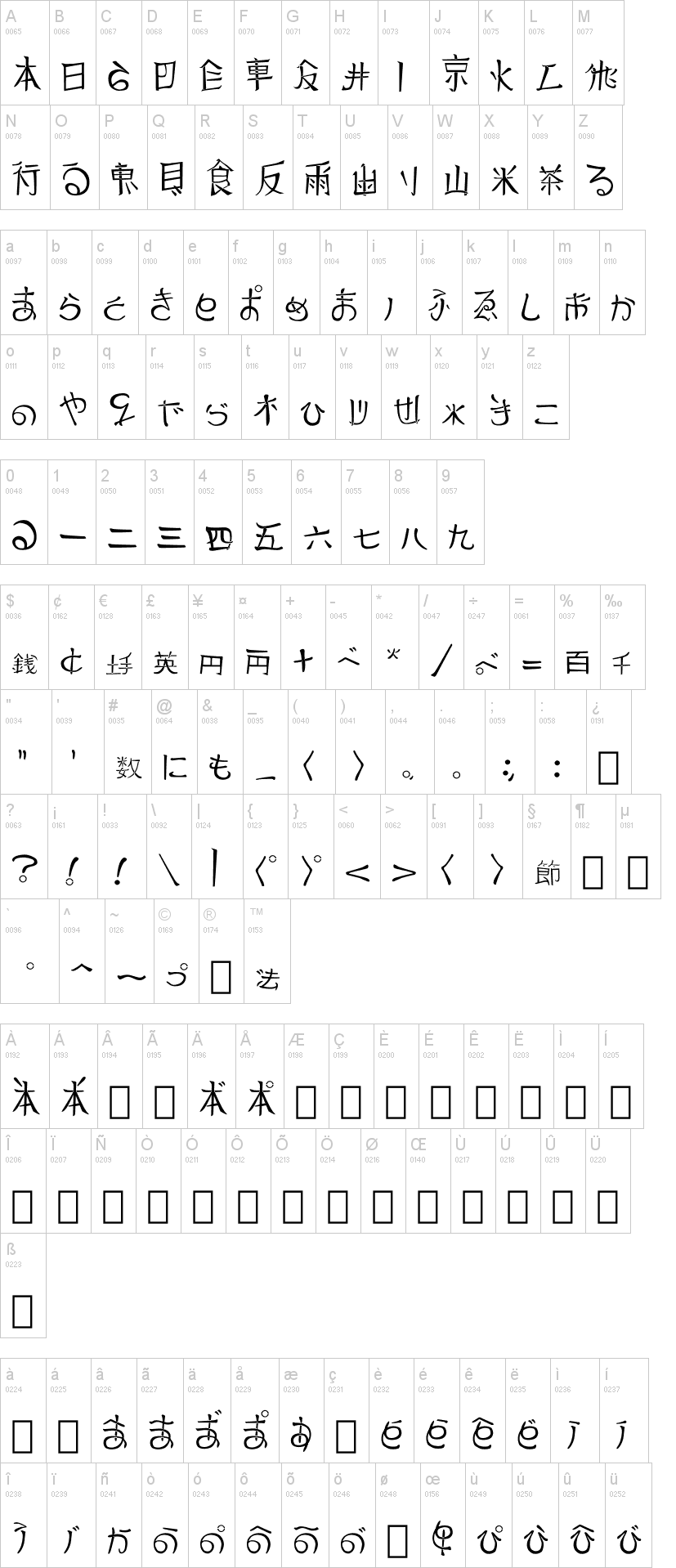
Reading From The East 是一种汉字字体,其设计灵感来自于东方传统文化和书法艺术。该字体的设计者是来自中国的设计师刘易阳,他从传统的书法艺术中汲取灵感,将其与现代设计理念相结合,创造出了一种既古老又现代的字体。 Reading From The East 字体的特点是优雅、简洁,但又不失有力量感。其笔画流畅、有韵律感,同时也能展现出汉字的独特美感。这种字体适用于书法、海报、包装设计、商标设计等领域,也非常适合用于中文版式排版中。 总之,Reading From The East 字体是一种融合了传统与现代、优雅与力量感的汉字字体,其具有独特的美感和应用价值。内容介绍
Reading From The East是一款非常不错的手写艺术字体,具有很好的视觉感,适合于文化类的宣传设计、商业类品牌的广告和产品包装设计以及个性化文字排版等较多场景。